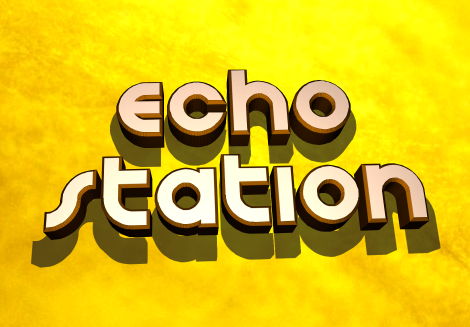
Introduzimos a família de fontes Echo Station! Uma nova família criada por iconian. Esteito sob uma abordagem minimalista e futurista, essa família de fontes se destaca como um incrível complemento para seus projetos de design. Com seu estilo clean e moderno, você pode usar Echo Station em uma variedade de aplicações gráficas, desde logomarcas e posters até ilustrações vintage e mockups customizados. A família é perfeitamente adaptada para qualquer projeto que esteja buscando um toque inovador e sofisticado no design de sua arte final. Seu design elegante e limpo torna Echo Station uma ótima adição à sua coleção de fontes, garantindo que seus trabalhos sempre estejam em alta estética. A família inclui vários pesos diferentes de negrito, itálico e obliquo para dar mais variação às suas criações. Seja para a sua próxima campanha publicitária ou projeto pessoal, Echo Station trará um toque único ao seu design. Com ela, você pode expressar inúmeras ideias e conceitos de uma maneira que se destaca. A família foi projetada com versatilidade em mente, permitindo que você crie designs atraentes e contemporâneos para diversos formatos de mídia. Além disso, Echo Station é um excelente exemplo da evolução das fontes serifadas para o estilo mais moderno e minimalista de sans serif.